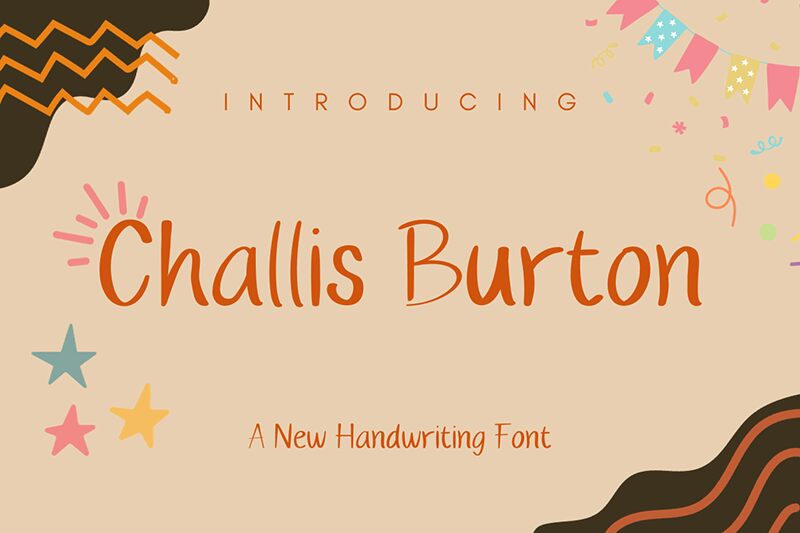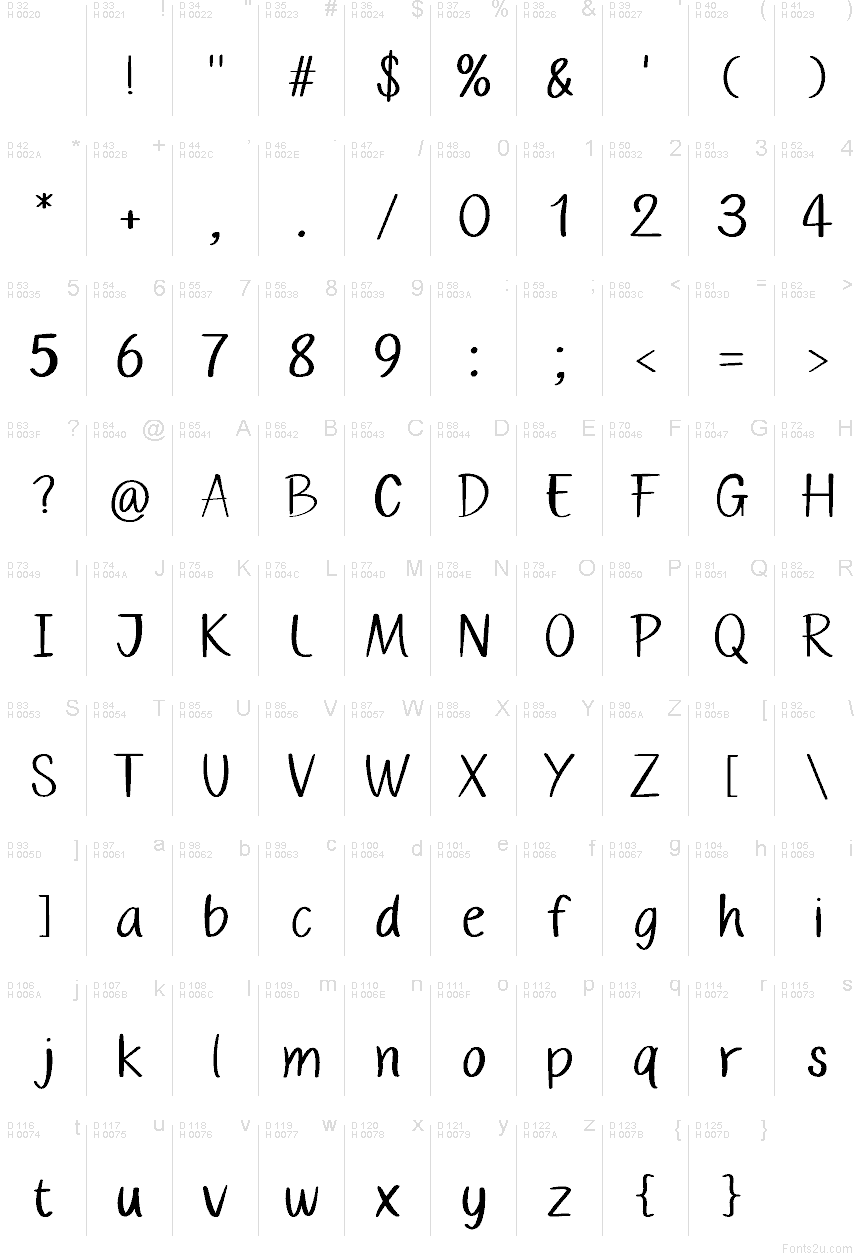
Challis Burton
Challis Burton от Insan Perkasya — это бесплатный рукописный шрифт с плавными линиями и узким, слегка наклоненным ритмом. Буквы выглядят естественно, будто нарисованы пером, а закругленные изгибы и высокий, элегантный силуэт придают тексту живость, не перегружая его лишней строгостью.
Challis Burton отлично подходит для свадебных приглашений, логотипов, брендинга в стиле «автограф», оформления цитат, открыток и постов в социальных сетях, где важен личный, рукописный акцент. Благодаря связному начертанию шрифт идеально смотрится в коротких заголовках, когда нужно создать впечатление быстрого, но аккуратно выполненного письма.